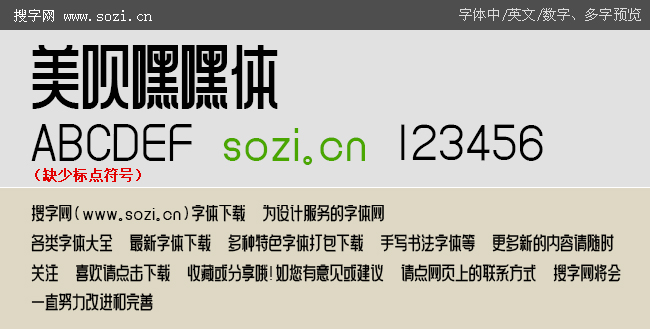
美唄嘿嘿體2.0
搜字網(wǎng)給大家提供一款美唄嘿嘿體2.0中文字體下載,美唄嘿嘿體是一款通用型強(qiáng)的的黑體字體,有著時(shí)尚、年輕、女性化氣質(zhì)。美唄嘿嘿體2.0版本字庫(kù)漢字和字符共計(jì)2631個(gè)。適用于平面宣傳設(shè)計(jì)、網(wǎng)頁(yè)設(shè)計(jì)、海報(bào)設(shè)計(jì)等應(yīng)用。